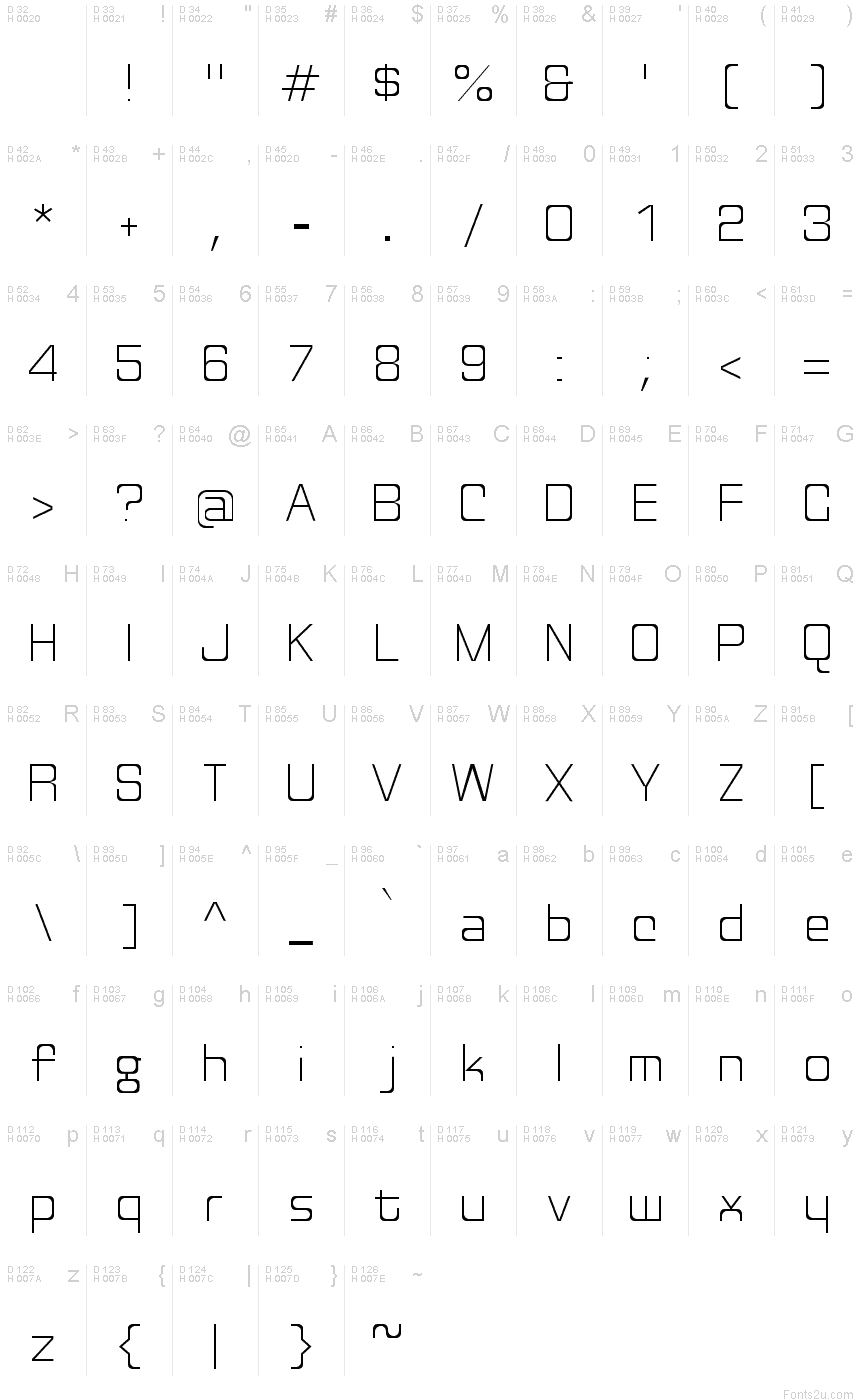
Discognate Light
Discognate Light od Tepid Monkey Fonts to nowoczesny, darmowy bezszeryfowy krój pisma, który od razu przywodzi na myśl neony, syntezatorowe linie i nocne ulotki. Jego cienkie, równe kreski tworzą zaokrąglone prostokąty i kanciaste pętle, nadając każdemu słowu gładki, rurowy wygląd – jakby świecący przewód został wygięty w kształt liter. Odstępy są szerokie i przewiewne, dzięki czemu nawet gęsty tekst pozostaje czytelny, zachowując jednocześnie elegancki i futurystyczny charakter.
Używając Discognate Light, nadasz spójny, klubowy wyraz swoim imprezom DJ-skim, okładkom albumów elektronicznych, ulotkom, plakatom w stylu arcade, wydarzeniom technologicznym czy retro-futurystycznym logotypom. Ten darmowy font świetnie sprawdza się w dużych nagłówkach, gdzie jego geometryczne krzywe są najlepiej widoczne; w tekście głównym zestaw go z prostym, neutralnym krojem bezszeryfowym, aby zachować przejrzystość i czytelność projektów.